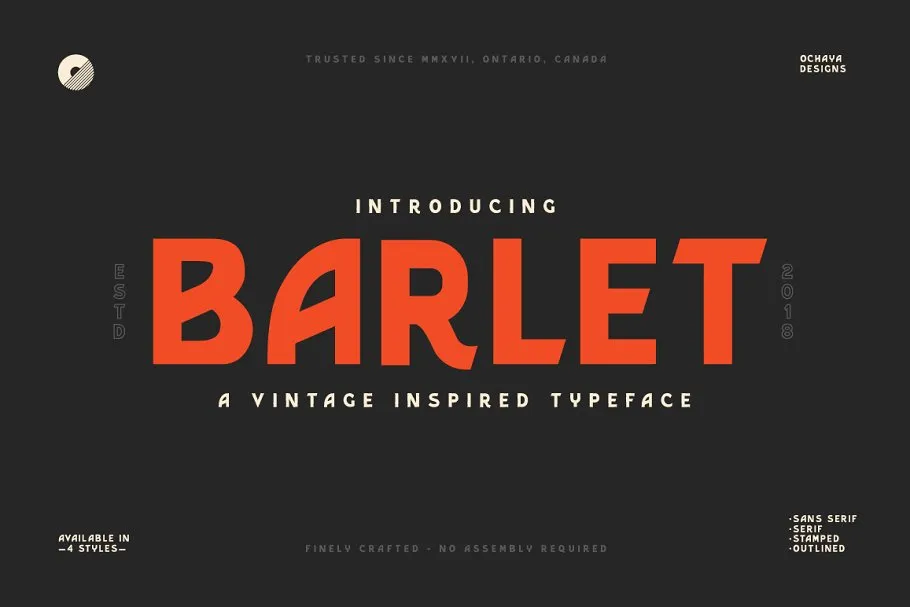
Convidamos você a explorar uma nova família de fontes originais do designer 0001themes, chamada Barlet Typeface. Esta elegante e vintage inspirada fonte sans serif é certamente algo que vai revolucionar seus projetos de design gráfico. Inspirada em designs antigos, o Barlet oferece quatro estilos vintage completos para usar em sua marca, design impresso, cabeçalhos de títulos e muito mais. O Barlet é perfeito para qualquer aplicação onde você precisará de uma fonte moderna e sofisticada. Experimente a Barlet Typeface hoje e transforme seus projetos!